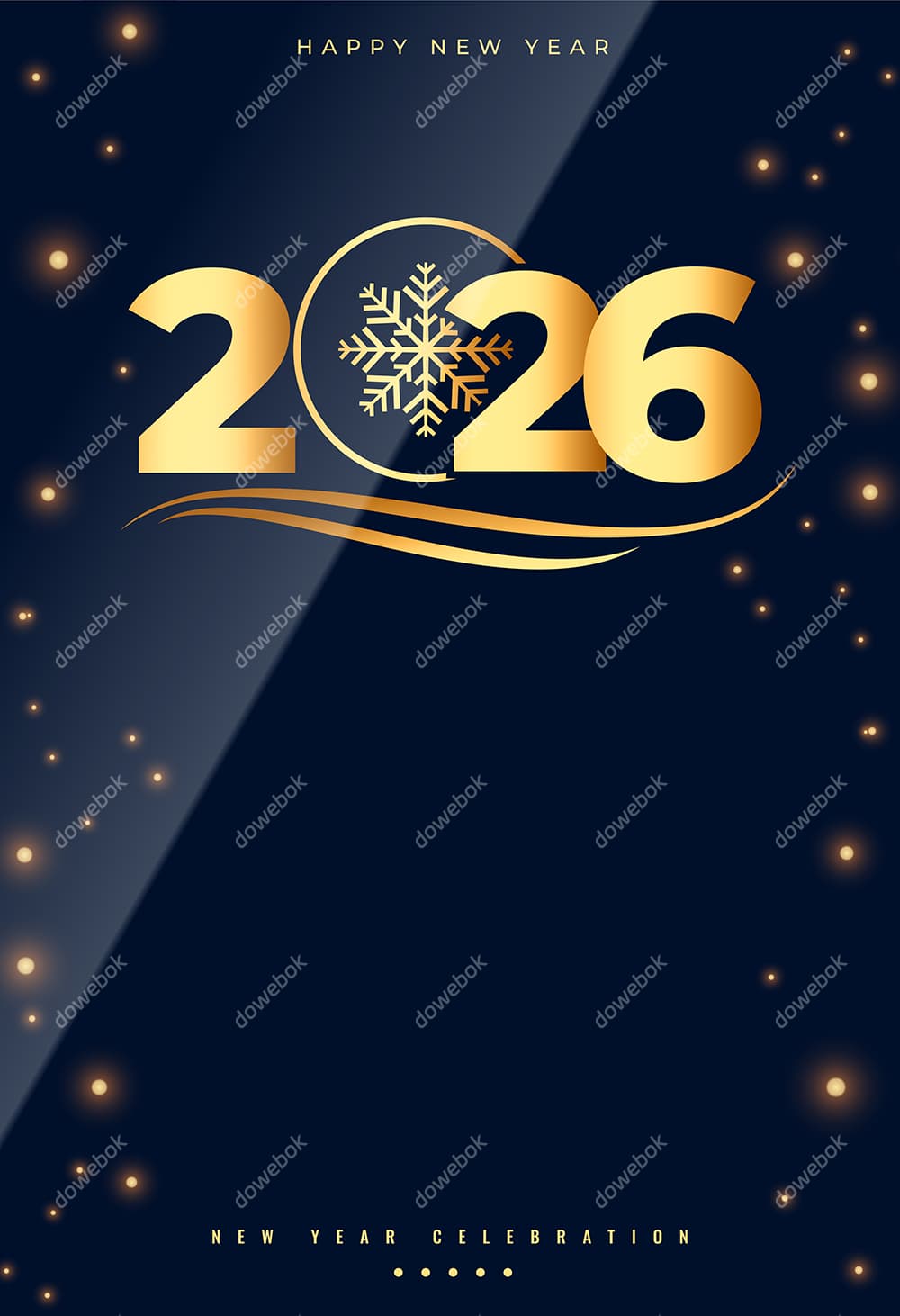
这是一款金色雪花和数字设计的 2026 新年快乐矢量素材,深幽暗蓝背景缀着暖光星点,鎏金 “2026” 字体间嵌着雪花纹圆饰,搭配柔美金色飘带,精致灵动。上下 “Happy New Year”“NEW YEAR CELEBRATION” 字样呼应主题,整体以蓝金配色融合冬日元素与闪耀细节,既显跨年的轻奢格调,又用暖光星点烘托出温馨的节日氛围,雅致且富有仪式感。